艺术字体可以在不同的时期流传,艺术字是一种对字形的结构进行加工使其变化的图片艺术,配以装饰,使其美轮美奂,目前许多大牌公司或品牌平台等均有其个性化的艺术字设计,立体艺术字、象形艺术字等均在其中,那么ps字体设计为什么会成为经典呢?为什么会被观众所记忆呢?
可以看一下“淘宝网”这三个艺术字,以至于我们在用它的笔画去设计别的艺术字的时候,别人看到就会问感觉这个艺术字是否根据淘宝网的艺术字来设计的,或者是照搬的、抄袭淘宝的艺术字,因为这个艺术字在我们的脑海里边已经根深蒂固,形成一种非常强烈的印象,这个艺术字沿用多年,一直没有进行改变,因为它足够成功,许多艺术字体ps不需要改变,这就是艺术字设计的魅力。
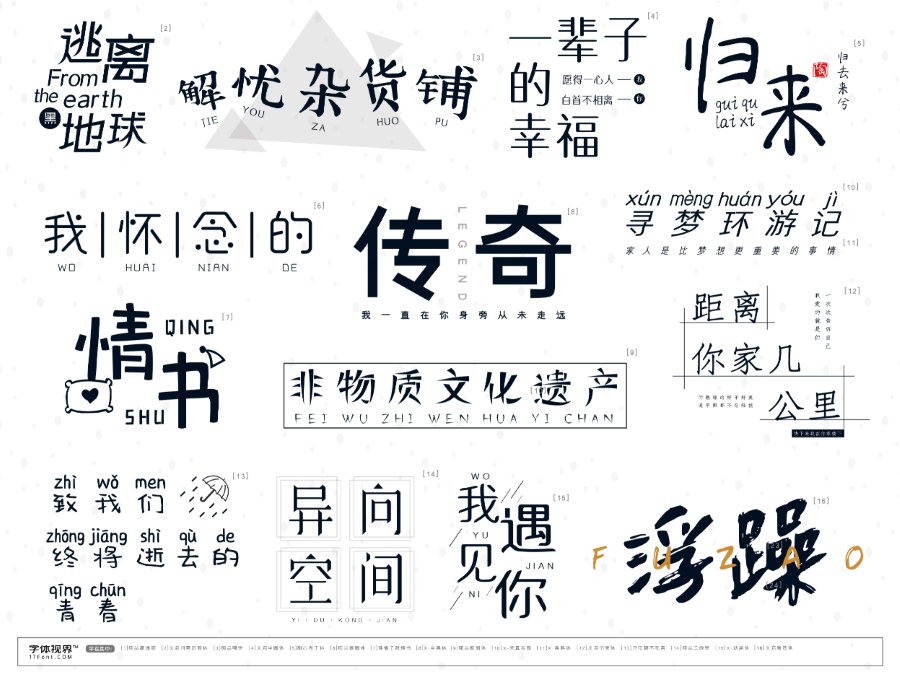
通过艺术字体ps典型的案例可知,以品牌名称的艺术字设计作为logo,它最大的优势在于易于识别和记忆,便于传播和推广,一些设计是中英文结合的,中间加入了一些小图形、小寓意在里边,再集合一些虚拟出来的意向,如果左边是一个图形logo,右边可以添加中文字,那就非常鲜明的把这个logo整体分成了两部分,第1部分是图形,第2部分是中文艺术字体转换器,无论这个图形做的有多么大众,多么平凡,它总是两部分,所以它在传播的时候就不会造成损耗。
从传播学的角度来说,艺术字体ps的记忆度高是因为它的书写规律不同,并不是传统的横平竖直,也并非要遵循外围方正端庄大方的思维定律,一些字体匀称,一些字体穿插争让,这便是艺术字的魅力。